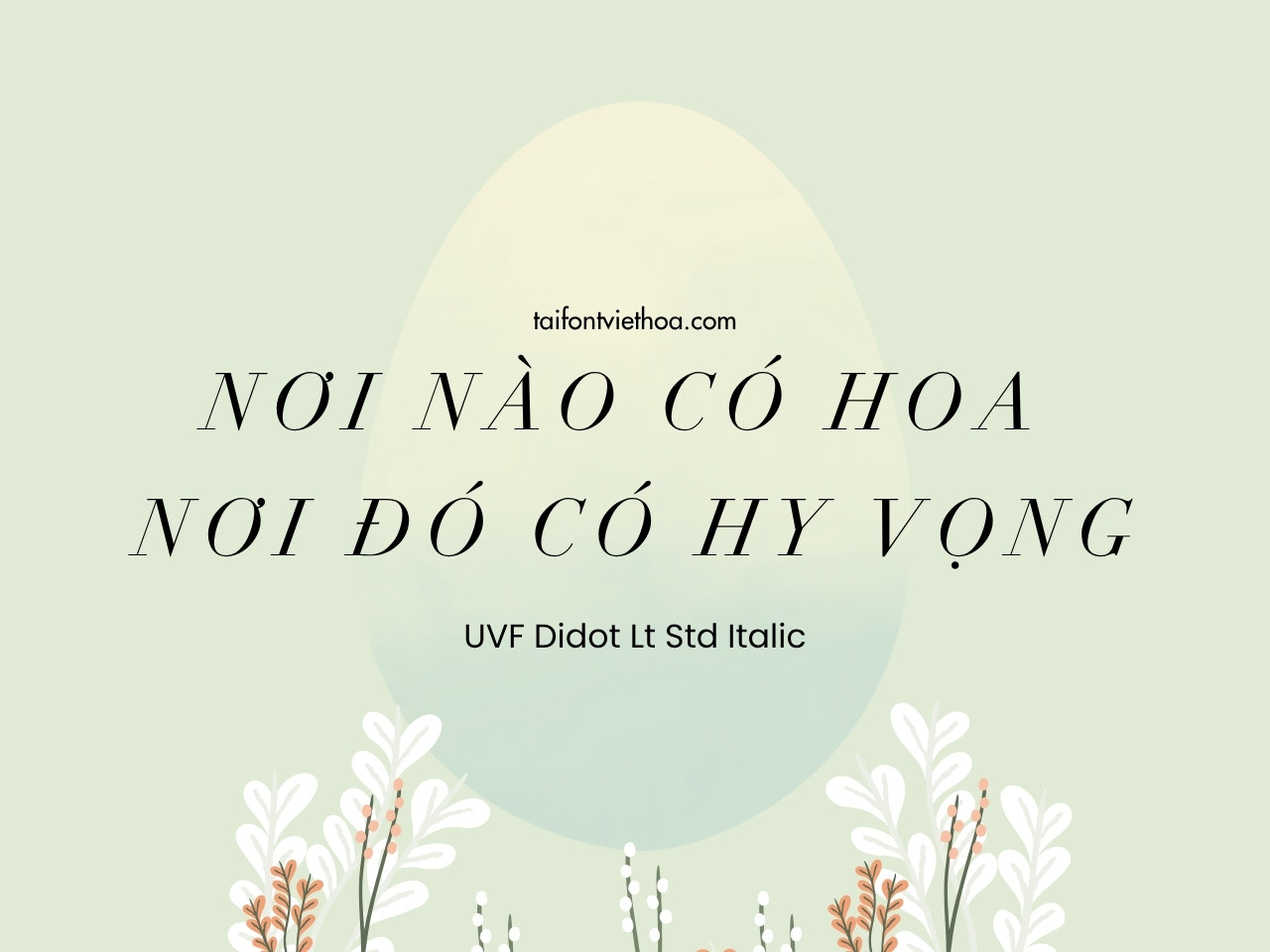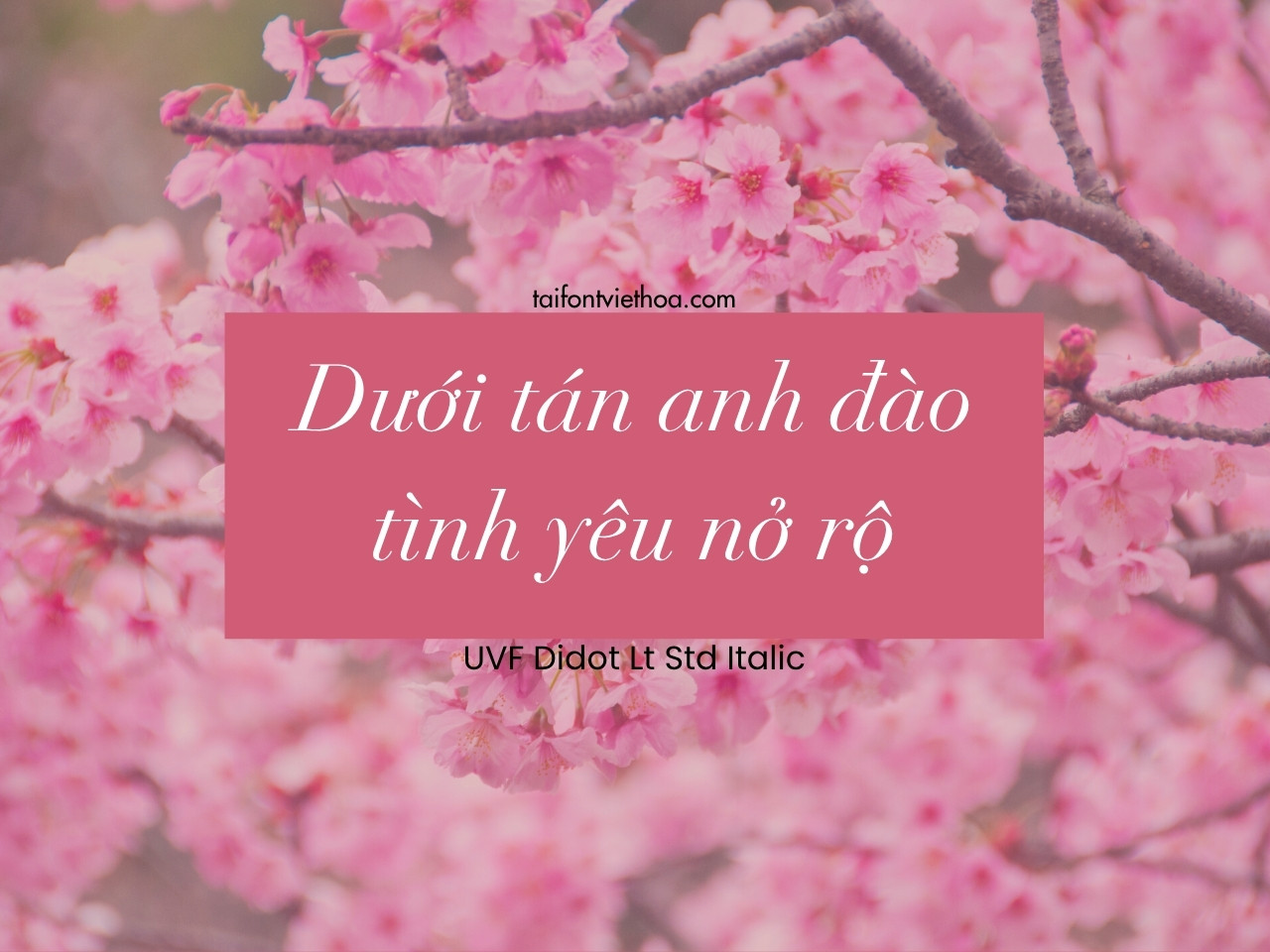
Font việt hóa UVF Didot Lt Std Italic
Giới thiệu về font UVF Didot Lt Std Italic
UVF Didot Lt Std Italic là biến thể nghiêng đầy duyên dáng của bộ font Didot danh tiếng – một kiểu chữ serif cổ điển xuất hiện từ thế kỷ 18 tại Pháp. Dòng họ Didot nổi tiếng với kiểu chữ có độ tương phản mạnh, đường hairline thanh mảnh kết hợp cùng các serif nhọn và tinh tế. Biến thể Italic của UVF Didot mang phong cách thanh lịch, giàu tính biên tập và phù hợp với những dự án mang phong thái cổ điển, nghệ thuật hoặc thời trang cao cấp. Font được sưu tầm và chia sẻ bởi thành viên Font Chuẩn, và được taifontviethoa.com sử dụng thực tế trong các thiết kế in ấn, biên tập tạp chí và branding đẳng cấp.
Đặc điểm thiết kế và ứng dụng của UVF Didot Lt Std Italic
Font sở hữu cấu trúc serif truyền thống với phần nét dày – nét mảnh rõ rệt, tạo nên sự tương phản sang trọng. Biến thể italic có độ nghiêng nhẹ nhàng, mang hơi hướng nữ tính và quý phái. Các chữ cái cao thanh, độ rộng hẹp cân đối giúp văn bản trở nên tinh tế mà vẫn dễ đọc. UVF Didot Lt Std Italic hỗ trợ đầy đủ tiếng Việt, sẵn sàng phục vụ các nhu cầu thiết kế cao cấp và chỉnh chu.
Ứng dụng lý tưởng: thiết kế tạp chí thời trang, in ấn mỹ thuật, biên tập sách cao cấp, logo thương hiệu mỹ phẩm hoặc danh thiếp cá nhân chuyên nghiệp. Ngành nghề phù hợp: thời trang, mỹ phẩm, nội thất cao cấp, xuất bản, truyền thông nghệ thuật và thương hiệu cao cấp.